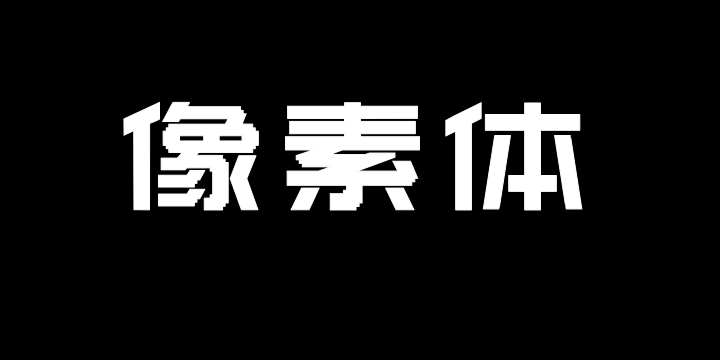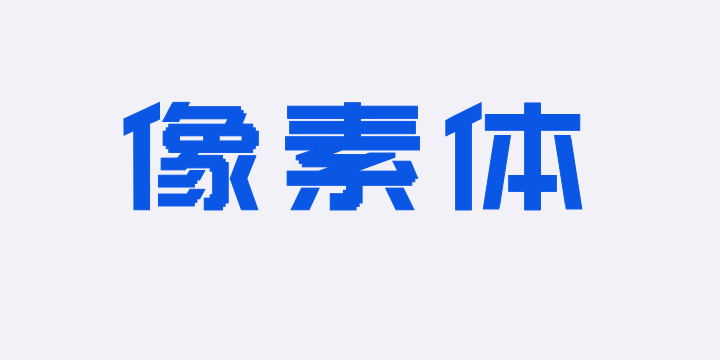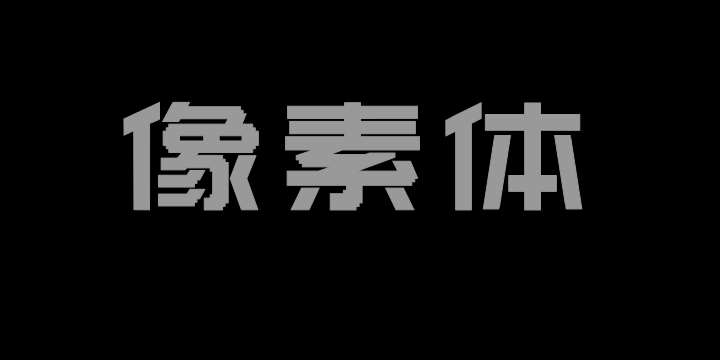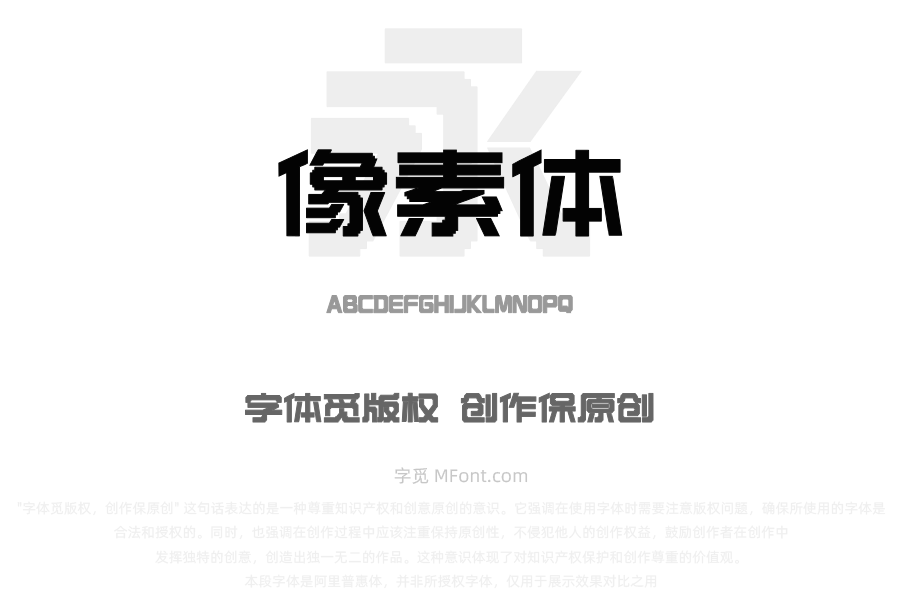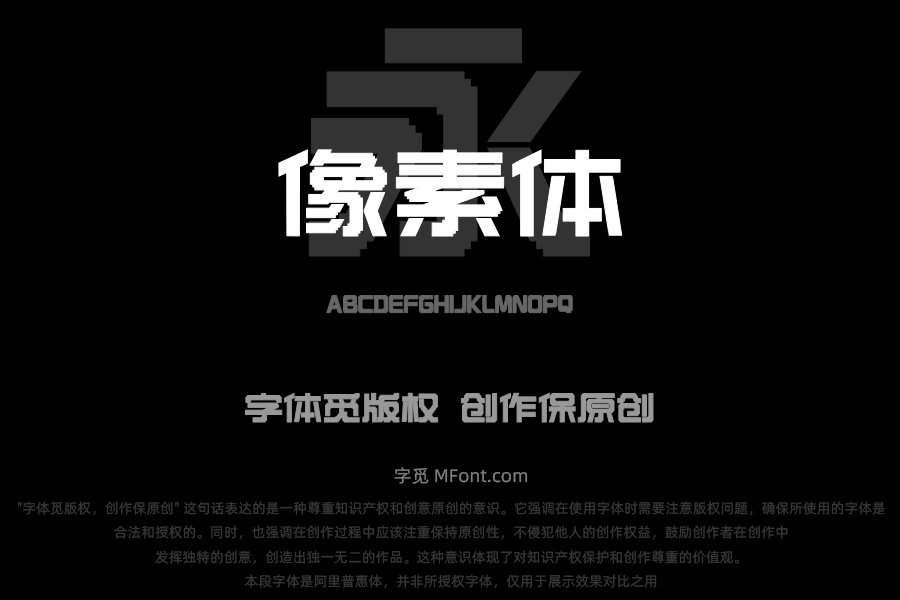
关于上首像素体字体字库信息
字体全名: 上首像素体
字体简介: 上首像素体,简体中文约6763字,“上首像素体”是一款融合复古情怀与现代美感的创意字体,灵感源于早期数字时代的像素点阵。字体以方形像素为基本单元,通过规则的网格结构构建笔画,笔画刻意呈现阶梯状转折,强化像素颗粒感,但通过优化比例与间距,确保阅读流畅性。转角处采用硬边处理,搭配均匀的负空间,形成独特的科技韵律。支持多级字重变化,从细线的精致感到粗体的力量感,兼顾屏幕显示与印刷需求。上首像素体兼具功能性与装饰性,适用于游戏UI、潮流海报、品牌标语等场景,以数字化触觉唤醒复古未来风的审美共鸣。